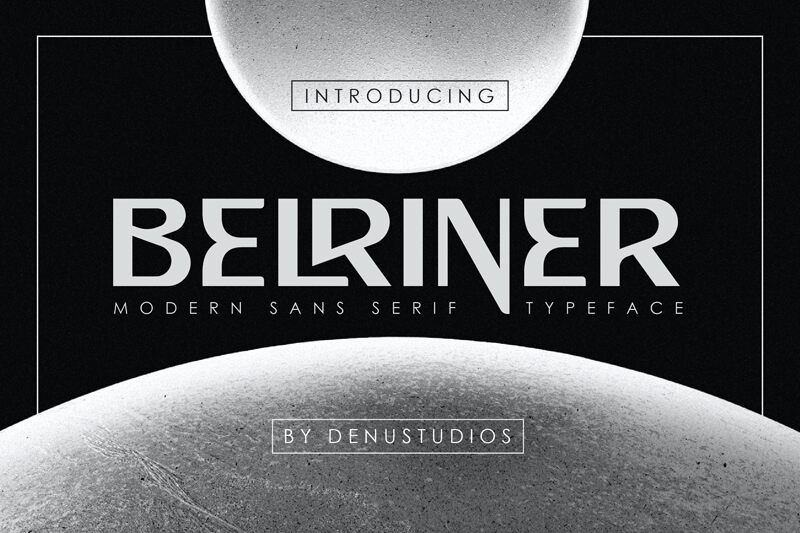
Belriner Italic od Denustudios je bezpatkové písmo zdarma, kterému dominuje rychlý, dopředu nakloněný rytmus a široké křivky střižené ostrými, úhlovými zlomy. Tato kombinace dodává písmu elegantní směr, zatímco zaoblené tvary a precizní spoje zajišťují, že působí výrazně a neotřele.
Belriner Italic skvěle vynikne na obalech hudebních alb, plakátových titulcích, sportovním brandingu, módních štítcích i v záhlavích sociálních sítí, kde krátká slova potřebují pohyb, aniž byste museli sahat po psacím písmu. Jeho zúžené tvary a ostré křivky dodávají logům i obalům napjatý, autorský vzhled, který se skvěle hodí pro názvy, slogany a kompaktní nadpisy.